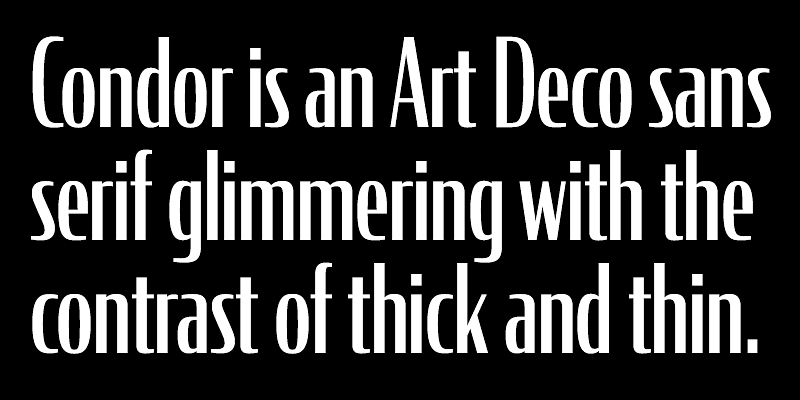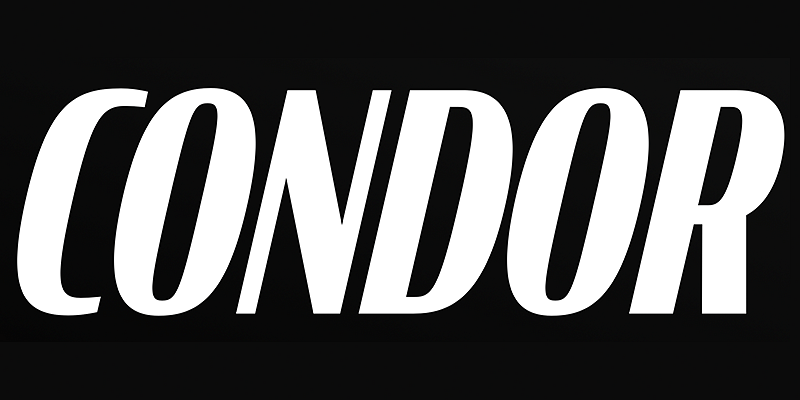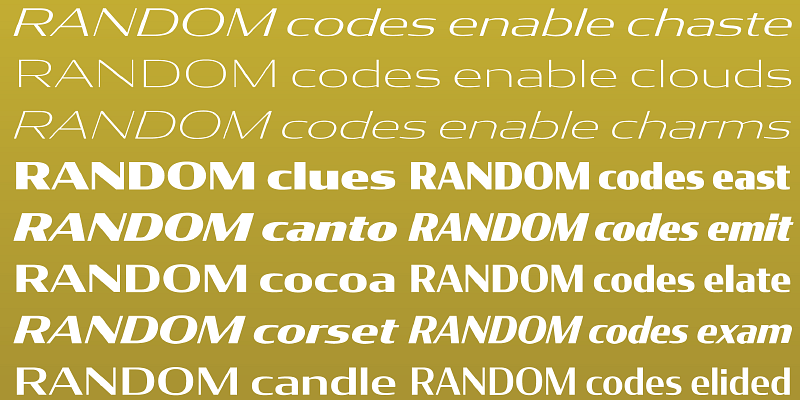
Inspiré à l’origine par le lettrage commercial et les monuments des années 20 et 30, David Jonathan Ross a fusionné un style très contrasté avec une structure rationalisée de courbes aplaties et de larges ouvertures pour créer cette famille de caractères sans empattement étincelante, aux légers accents Art déco. Condor a une envergure inhabituellement large : des graisses compactes tendues qui exhibent une énergie athlétique et des styles brillants et aériens pour rayonner de luxueux raffinement.